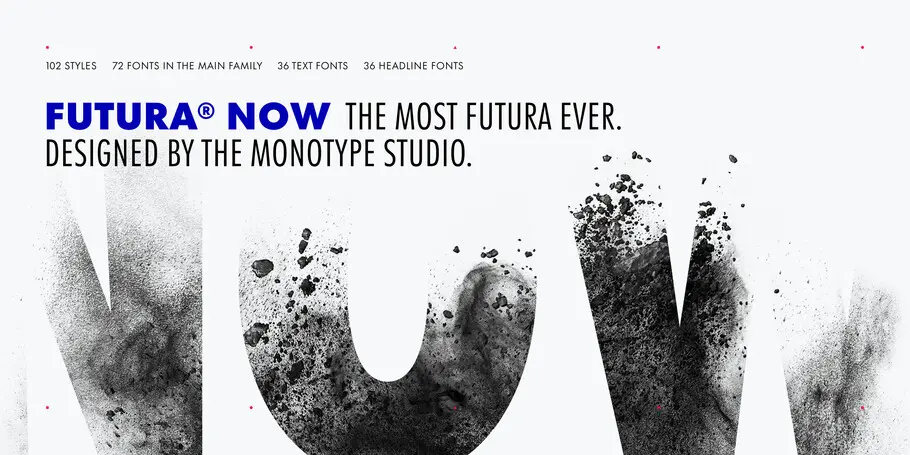
Le nouveau siècle de Futura.
“ Nous nous sommes posé la question : de quoi cette famille a réellement besoin, aujourd’hui ? Quelle serait la meilleure version de Futura pour les cinquante ou cent prochaines années à venir ? Et c’est ce que nous avons entrepris de créer. ”
Juan Villanueva, designer typographique.
Il serait difficile d’imaginer le XXe siècle sans Futura. Lancée par la fonderie Bauer en 1927, Futura de Paul Renner a rencontré un succès presque instantané, et très vite, elle s’est imposée comme un élément emblématique et immuable de notre culture commune.
Futura est intemporelle, dans le sens le plus pur du terme. C’est un vrai caméléon typographique : parfait « à la maison, à côté d’un séquoia autant que d’une table en inox », comme le dit Steve Matteson, directeur de la création typographique chez Monotype.
Mais le XXe siècle est maintenant révolu. L’ère de l’imprimé, dans laquelle Futura a connu des heures prospères, a laissé place à quelques décennies de progrès numériques, pour lesquels elle est mal équipée. Ironiquement, Futura elle-même — adaptable, austère et saturée de nostalgie — s’avère plus populaire et indispensable que jamais. De bien des façons, elle est un parfait contrepoids esthétique à notre culture obsédée par la technologie.
À quoi pourrait ressembler une Futura du XXIe siècle ? Elle serait optimisée pour la lecture sur écran, qu’il s’agisse de grands écrans OLED haute résolution ou de minuscules montres intelligentes. Elle offrirait des graisses dessinées avec précaution pour tous les usages et une attention renouvelée pour l’espacement. Elle inclurait une police variable pour un maximum de flexibilité et la possibilité d’affiner les designs. Enfin, elle engloberait l’histoire entière de Futura en une seule version, incluant ses ramifications non conventionnelles comme les styles Script ou Display.
On dirait bien Futura Now.
Pas d’assemblage nécessaire.
Terrance Weinzierl, membre de l’équipe créative de Futura Now, le souligne : « L’élément essentiel avec Futura Now, c’est qu’elle est facile et prête à l’emploi. » Cela n’a pas l’air de grand chose, mais les versions précédentes de Futura peuvent amener un « parcours mouvementé » selon lui. Espacements incohérents, éventail de graisses limité, obliques déformés et support linguistique éparpillé sont de réelles limites à la capacité de Futura de s’adapter aux besoins des marques modernes et numériques. « Regardez de plus près notre coupe Linotype de Futura, par exemple, et vous verrez qu’il y a en effet quelque chose d’un peu décalé. Il faut l’utiliser avec précaution. »
“ L’élément essentiel avec Futura Now, c’est qu’elle est facile et prête à l’emploi. ”
Terrance Weinzierl, designer typographique senior.
L’élément essentiel qui rend Futura Now facile à utiliser, ce sont sont les tailles optiques de la typographie — Futura Now Text et Futura Now Headline. Dans certains cas, pour optimiser la lisibilité sur des tailles de point et distances de lecture, les tailles optiques sont créées en reprenant le dessin des lettres. Tandis que, pour sa part, le dimensionnement optique de Futura s’est concentré uniquement sur les questions d’espacement mentionnées plus haut.
Comme son nom l’indique, Futura Now Text est parfaite pour la lecture prolongée car généreuse en espacements. Les formes classiques des lettres de Futura disposent d’un peu plus de place pour respirer sur la page et, surtout, sur écran. On peut particulièrement le remarquer sur les graisses les plus fines, où davantage d’espace vide permet aux déliés subtils de se démarquer. Futura Now Headline resserre juste un peu l’espacement, pour gagner de la place dans les cadres de textes limités autant que pour rester fidèle à l’impact visuel qui a fait de Futura la favorite des artistes et des publicitaires.
« L’espacement est une partie incontournable du design », raconte Juan Villanueva, designer typographique chez Monotype, qui a également travaillé sur Futura Now. « Le fait d’ajouter un simple petit espacement peut rendre une police tellement plus lisible sous différentes tailles. »
Si ces ajustements ont une influence en impression, ils laissent une réelle empreinte dans le design numérique. « La qualité sur écran rattrape le papier », explique Weinzierl. « En 1995, les écrans étaient si sommaires que l’on ne pouvait pas voir les tailles optiques si on les avait. Aujourd’hui, nous avons aux poignets des écrans de 400 dpi. Autant dire, une multitude de pixels supplémentaires avec lesquels travailler. » Le dimensionnement optique tire pleinement parti de ces pixels en délivrant une lisibilité absolue, dans presque tous les environnements numériques.
“ L’espacement est une partie incontournable du design. Le fait d’ajouter un simple petit espacement peut rendre une police tellement plus lisible sous différentes tailles. ”
Juan Villanueva, designer typographique.
Futura Now contient également la toute première police variable de Futura, disponible en sous-familles Text et Headline (qui sont combinées), Display et Script. Les polices variables peuvent être développées de deux façons : séparément ou bien en complément de polices existantes. Mais Futura Now est « née en tant que variable », selon Weinzierl, qui explique que ces polices variables ont été conçues depuis le début, pour s’assembler exactement aux versions statiques.
« Ce que nous avons fait, c’est que nous avons porté notre regard sur l’univers entier de Futura. Nous l’avons nettoyé et remis en ordre pour qu’il puisse être compris par les personnes qui utilisent les polices aujourd’hui », explique Villanueva. « Nous nous sommes posé la question : de quoi cette famille a réellement besoin, aujourd’hui ? Quelle serait la meilleure version de Futura pour les cinquante ou cent prochaines années à venir ? Et c’est ce que nous avons entrepris de créer. »